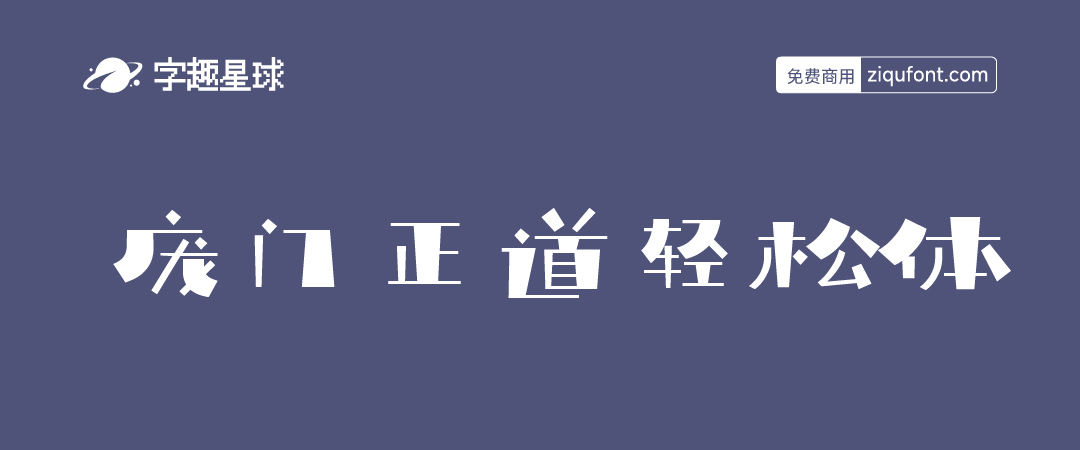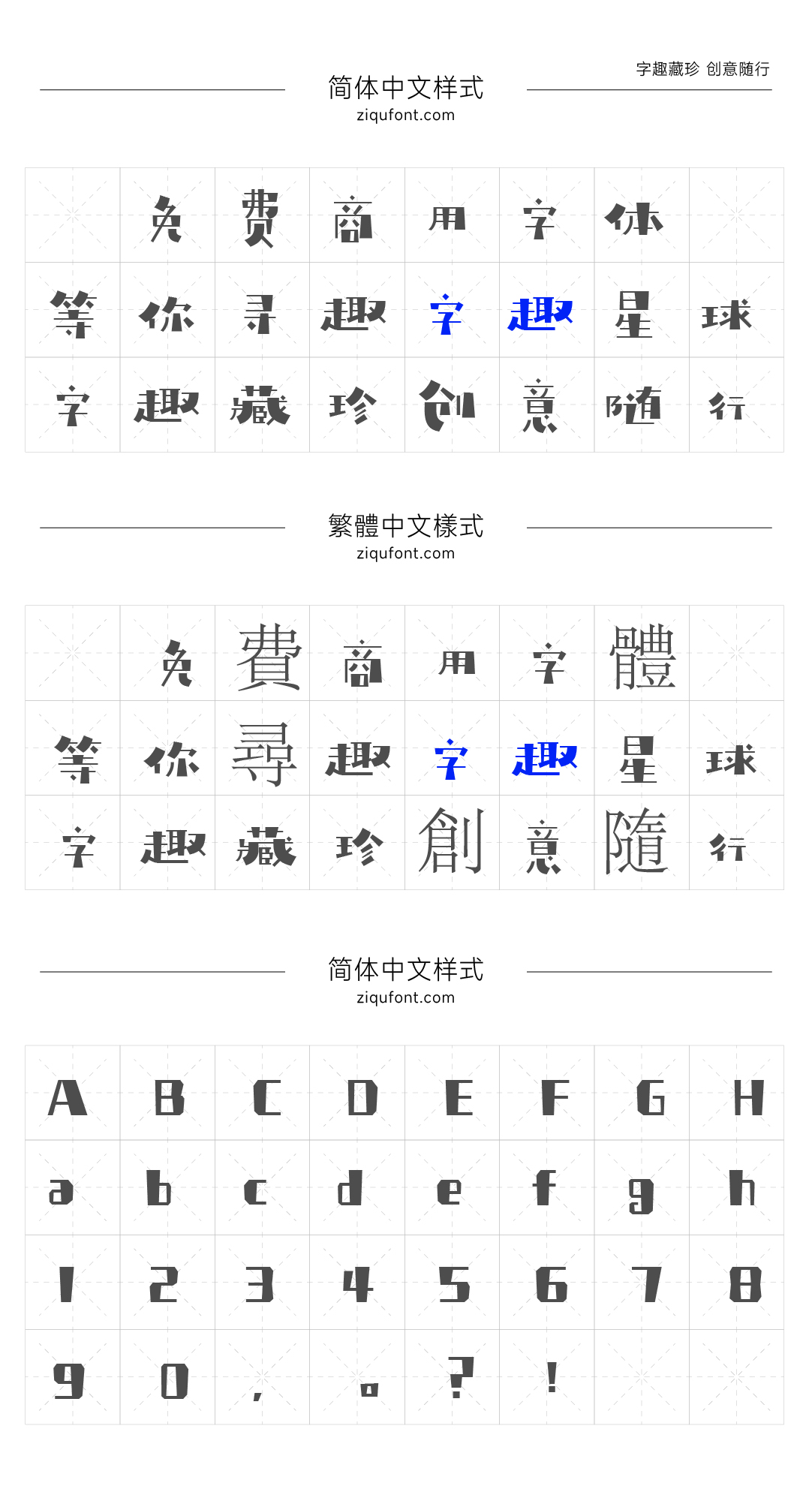
庞门正道轻松体
庞门正道的第三款免费字体,它就是非常的轻松、可爱,带着些许的俏皮的庞门正道轻松体。2019 年,庞门正道兵克字体设计班的学生,在自愿的原则下,一共 80 位学员参与了这款全新的免费字库的开发中。 在这里感谢这 80 位为庞门正道轻松体付出的可爱的人们,他们都是和我们一样,在一个平凡的设计师岗位上,平凡的收入水平,但是愿意额外付出时间来完成这个壮举,给大家在日常设计中可以多一种字体选择,谢谢。 重要的事情说三遍,这款「庞门正道轻松体」商用免费!商用免费!商用免费!